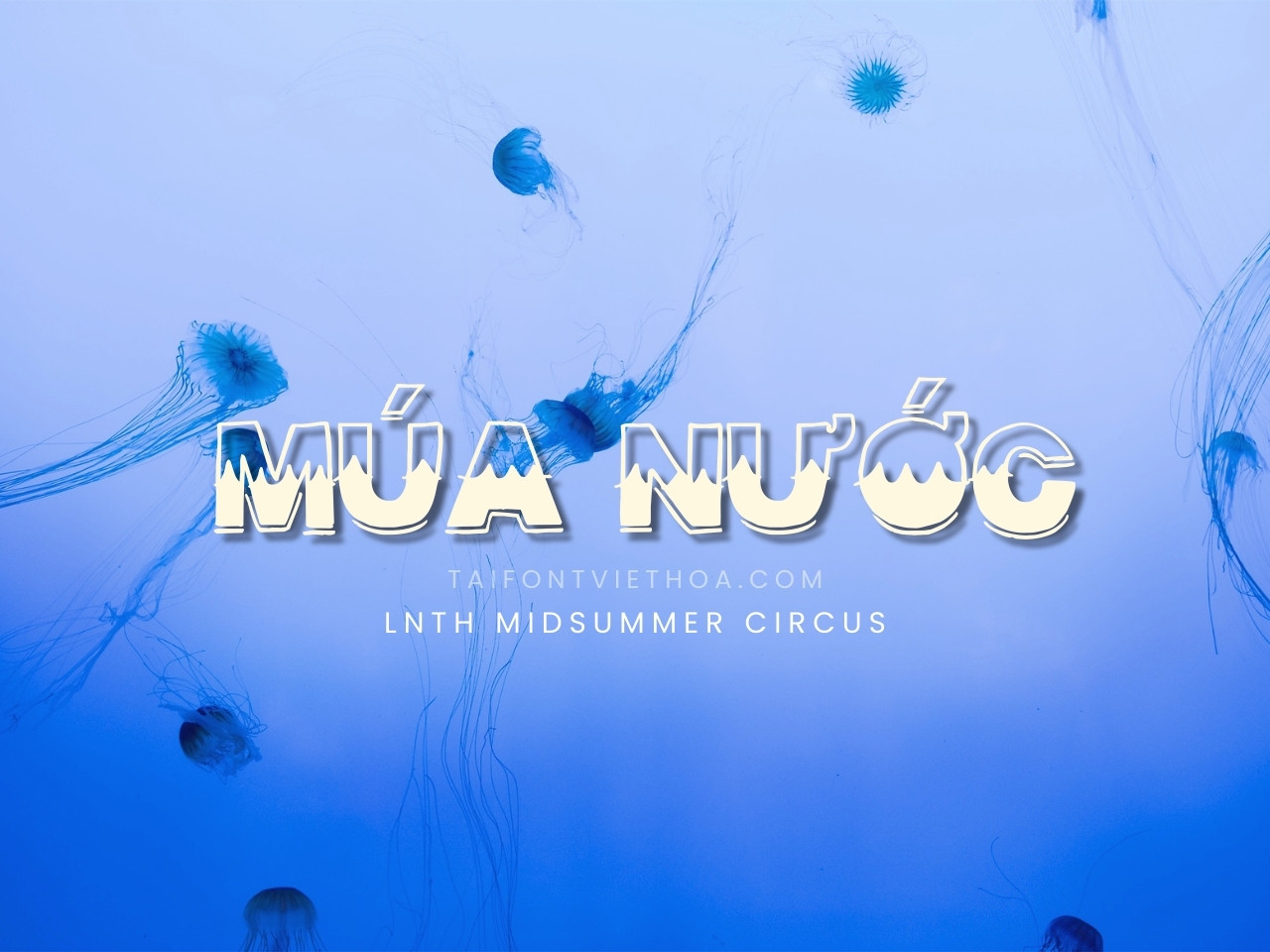
Font việt hóa LNTH Midsummer Circus
Giới thiệu về font LNTH Midsummer Circus – Cảm hứng xiếc cổ điển, sống động và vui nhộn
LNTH Midsummer Circus là phiên bản Việt hóa từ font “Midsummer Circus” do Skyhaven Fonts thiết kế. Kiểu chữ này lấy cảm hứng từ không khí rộn ràng, đầy màu sắc của rạp xiếc cổ điển châu Âu – với các đường nét cong mạnh, trang trí tinh tế và giàu tính nghệ thuật. Phiên bản Việt hóa được Tuỳn Pucca thực hiện, hỗ trợ tiếng Việt đầy đủ và hơn 60 ngôn ngữ quốc tế, giúp mở rộng khả năng ứng dụng trong các dự án toàn cầu nhưng vẫn giữ được bản sắc thiết kế độc đáo.
Font đã được taifontviethoa.com sưu tầm, chọn lọc và thử nghiệm thực tế với nhiều ứng dụng liên quan đến sự kiện, lễ hội, sân khấu và truyền thông giải trí. Đây là font lý tưởng dành cho những ai cần mang lại cảm giác sinh động, cổ điển và đậm dấu ấn thị giác trong các thiết kế sáng tạo.
Đặc điểm thiết kế và ứng dụng của LNTH Midsummer Circus
LNTH Midsummer Circus mang phong cách display cổ điển – với các ký tự trang trí đậm nét, hình dáng uốn lượn, có độ đậm và độ cao khác biệt. Các nét chữ được tô điểm bằng họa tiết xiếc truyền thống, tạo cảm giác vui nhộn, sống động và mang yếu tố hoài niệm. Đây là font dạng trình bày mạnh, phù hợp cho tiêu đề lớn, poster sự kiện, hay bảng hiệu sân khấu.
Ứng dụng lý tưởng của font bao gồm: thiết kế poster sự kiện, lễ hội sân khấu, chương trình truyền hình, banner tiệc sinh nhật, quảng cáo trò chơi hoặc nhận diện thương hiệu giải trí. Các ngành phù hợp: tổ chức sự kiện, truyền thông, giải trí, giáo dục nghệ thuật, đồ chơi trẻ em hoặc thương hiệu sáng tạo mang tính cổ tích.